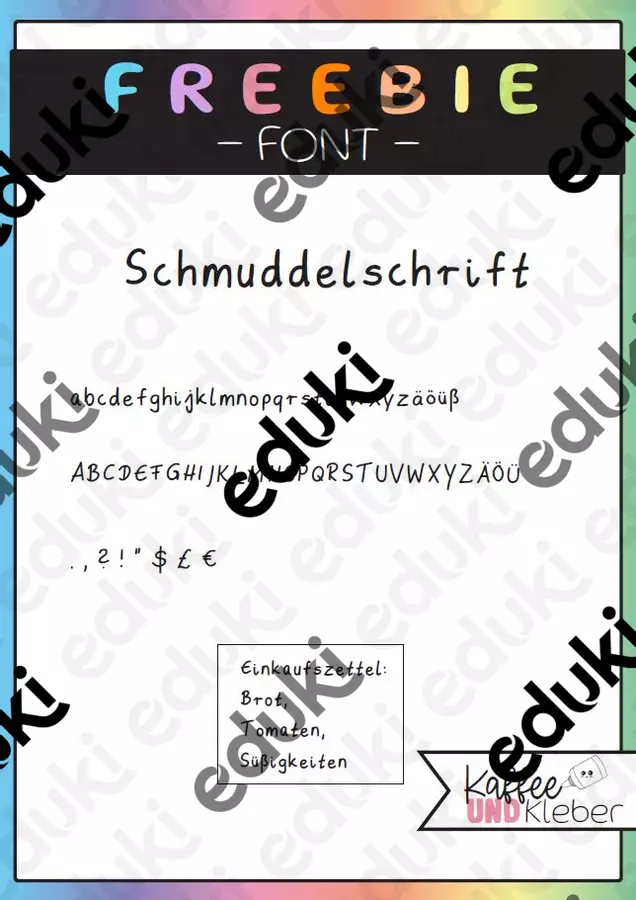
Eine schmuddelige Schriftart mit Handschriftcharakter.
Sie eignet sich z.B. als handschriftliches Element auf Arbeitsblättern:
- Schatzkarten
- geheimnisvolle Briefe
- Notizzettel
Font: Schmuddelschrift by Kaffee&Kleber